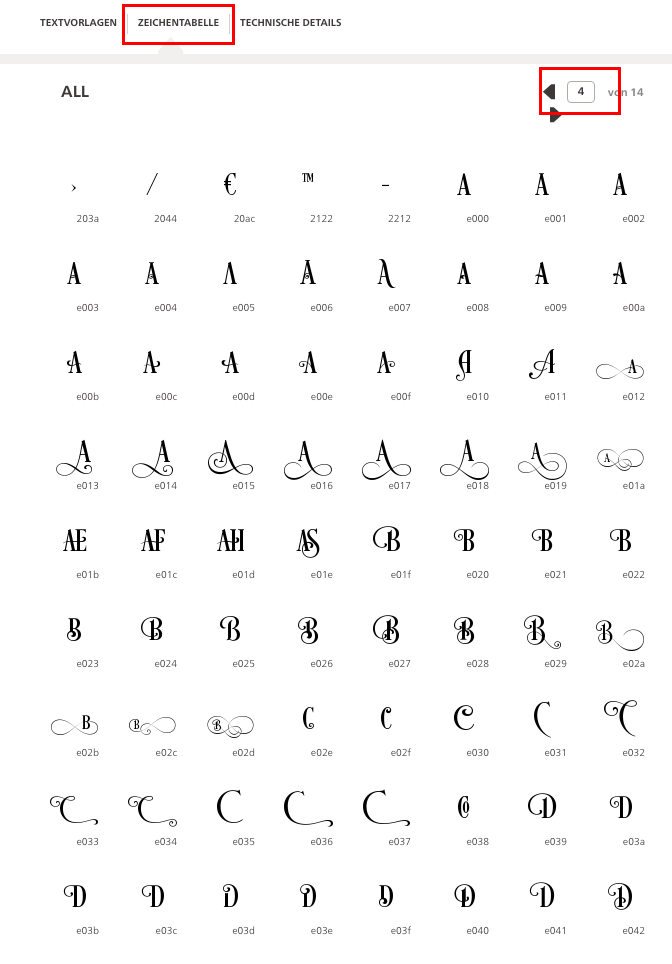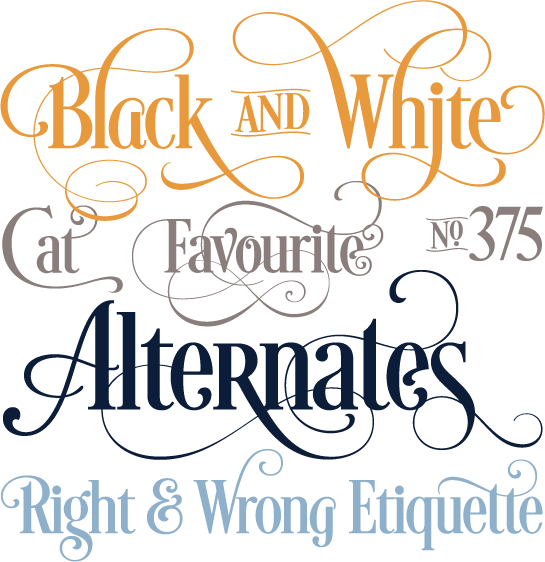
Zierschrift erstellen
Ich würde gerne eine Headline in einer Zierschrift setzen. Ich sehe das immer wieder auf z.B. Buchcover und frage mich jedes Mal, wie die das gemacht haben. Denn entsprechende Schriften finde ich einfach nicht. Das angehängte Bild stammt von Linotype, aber wenn ich diese Schrift kaufen möchte, werde ich zur normalen Serifenschrift geleitet, ohne diese ganzen Zierschlenkerer. Macht man die dann per Hand im Illustrator? Aber so symetrisch wie die sind, muss es da ja eine Technik geben.
Weiß von euch jemand, wie man eine Headline so hinbekommt, kennt ihr vielleicht ein Tutorial?
Wenn du bei Linotype die Schrift anwählst, kannst du auf der nächsten Seite die "Zeichentabelle" aufrufen, dort ab Seite 4 sind die Alternativbuchstaben zu sehen. Diese sind im Font enthalten und können über die Unicode-Eingabe, die Glyphenpalette in Adobe-Apps oder Opentype-Alternativen (siehe Roberts post darunter) etc. verwendet werden.